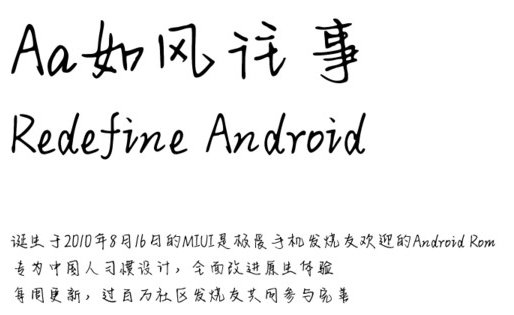
Aa如風(fēng)往事字體ttf是字體管家退出的一款大方質(zhì)樸的手寫字體,自己清秀而下筆有神,極具鋼筆書法字體的神韻,給人一種回味無窮的大方體驗,快來綠色資源網(wǎng)試試吧!
如風(fēng)往事字體,有著輕柔干凈的筆觸,給人十分清爽舒適的視覺呈現(xiàn),往事如風(fēng)追憶無窮,讓你的藝術(shù)設(shè)計更有內(nèi)容,在平面設(shè)計、包裝設(shè)計上使用也很出色。